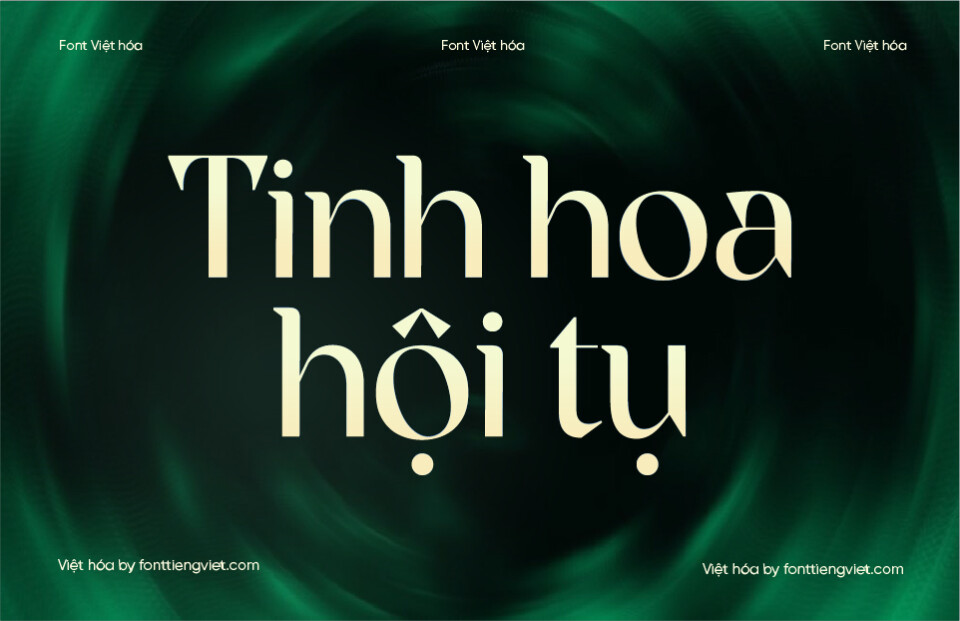
Font Việt hóa 1FTV VIP Rogie
Giới thiệu về Font Việt hóa 1FTV VIP Rogie trong thiết kế
Trong thế giới sáng tạo nội dung hiện đại, việc lựa chọn một bộ font chữ phù hợp đóng vai trò then chốt giúp truyền tải thông điệp một cách hiệu quả nhất. Bộ Font Việt hóa 1FTV VIP Rogie nổi lên như một sự lựa chọn hàng đầu cho những nhà thiết kế đang tìm kiếm sự kết hợp hoàn hảo giữa nét cổ điển và hơi thở hiện đại. Đây là một phông chữ thuộc phong cách Serif tinh tế, mang đến cảm giác sang trọng nhưng không kém phần gần gũi. Khi sử dụng Font Miễn Phí để thiết kế bài giảng, làm báo cáo hay tạo các ấn phẩm truyền thông học đường, bạn sẽ thấy sự khác biệt rõ rệt về mặt thẩm mỹ. Bộ phông này đã được tinh chỉnh kỹ lưỡng về dấu tiếng Việt, đảm bảo không xảy ra lỗi hiển thị khi soạn thảo văn bản trên các phần mềm đồ họa chuyên nghiệp như Adobe Photoshop, Illustrator hay thậm chí là các ứng dụng văn phòng cơ bản.
Đặc điểm nổi bật của bộ Font Việt hóa 1FTV VIP Rogie
Thiết kế thanh lịch và linh hoạt
Đặc trưng lớn nhất của Font Việt hóa 1FTV VIP Rogie chính là cấu trúc đường nét thanh mảnh nhưng vô cùng chắc chắn. Các chân chữ được thiết kế mềm mại giúp mắt người đọc dễ dàng lướt qua các dòng chữ mà không cảm thấy mỏi. Điều này đặc biệt hữu ích cho các bạn học sinh khi trình bày bài thuyết trình hoặc các thầy cô giáo khi soạn giáo án điện tử. Phông chữ này không chỉ đẹp ở các tiêu đề lớn mà còn giữ được độ sắc nét đáng kinh ngạc khi trình bày ở dạng đoạn văn bản nhỏ. Sự cân bằng giữa các khoảng cách ký tự giúp cho tổng thể thiết kế trở nên thông thoáng, chuyên nghiệp và bắt mắt hơn bao giờ hết.
Tối ưu hóa hoàn toàn cho tiếng Việt
Một trong những nỗi lo lớn nhất của người dùng Việt Nam là lỗi font khi có các dấu hỏi, ngã, nặng. Tuy nhiên, với Font Việt hóa 1FTV VIP Rogie, mọi ký tự đặc biệt trong bảng chữ cái tiếng Việt đều được xử lý chuẩn xác. Các dấu được đặt ở vị trí hợp lý, không quá cao cũng không quá thấp, tạo nên sự hài hòa tuyệt đối. Điều này giúp tiết kiệm thời gian chỉnh sửa thủ công và tăng hiệu suất làm việc cho các designer. Bạn có thể tự tin sử dụng bộ font này cho các dự án yêu cầu tính thẩm mỹ cao như thiết kế logo, bìa sách, hay các thiệp mời sự kiện tại trường học mà không cần lo lắng về vấn đề kỹ thuật.
Cách ứng dụng Font Việt hóa 1FTV VIP Rogie hiệu quả nhất
Để phát huy tối đa vẻ đẹp của Font Việt hóa 1FTV VIP Rogie, người dùng nên kết hợp nó với những tông màu trung tính hoặc các phông chữ không chân (Sans-serif) đơn giản để tạo sự tương phản. Trong các dự án học đường, bạn có thể dùng phông này cho các tiêu đề chính để tạo điểm nhấn nghệ thuật, thu hút sự chú ý ngay từ cái nhìn đầu tiên. Ngoài ra, việc điều chỉnh khoảng cách dòng (leading) rộng hơn một chút sẽ giúp văn bản trông sang trọng hơn. Hãy nhớ rằng, một bộ font đẹp chỉ thực sự tỏa sáng khi nó được đặt đúng ngữ cảnh và có sự đồng nhất với chủ đề chung của toàn bộ tác phẩm thiết kế.
Kết luận về giá trị của bộ font chữ VIP này
Hy vọng rằng bộ Font Việt hóa 1FTV VIP Rogie sẽ trở thành một công cụ đắc lực trong kho tài nguyên sáng tạo của bạn. Với sự tinh tế trong từng đường nét và khả năng hiển thị tiếng Việt hoàn hảo, đây chắc chắn là một mảnh ghép không thể thiếu để nâng tầm các dự án cá nhân cũng như tập thể. Việc sử dụng những bộ Font Miễn Phí, Font Việt Hóa, Font Việt hóa 1FTV VIP Rogie chất lượng không chỉ giúp sản phẩm đẹp hơn mà còn thể hiện sự chỉn chu và tôn trọng đối với người xem. Hãy bắt đầu trải nghiệm và tạo ra những tác phẩm ấn tượng ngay từ hôm nay để thấy được sức mạnh của nghệ thuật chữ viết trong truyền thông.